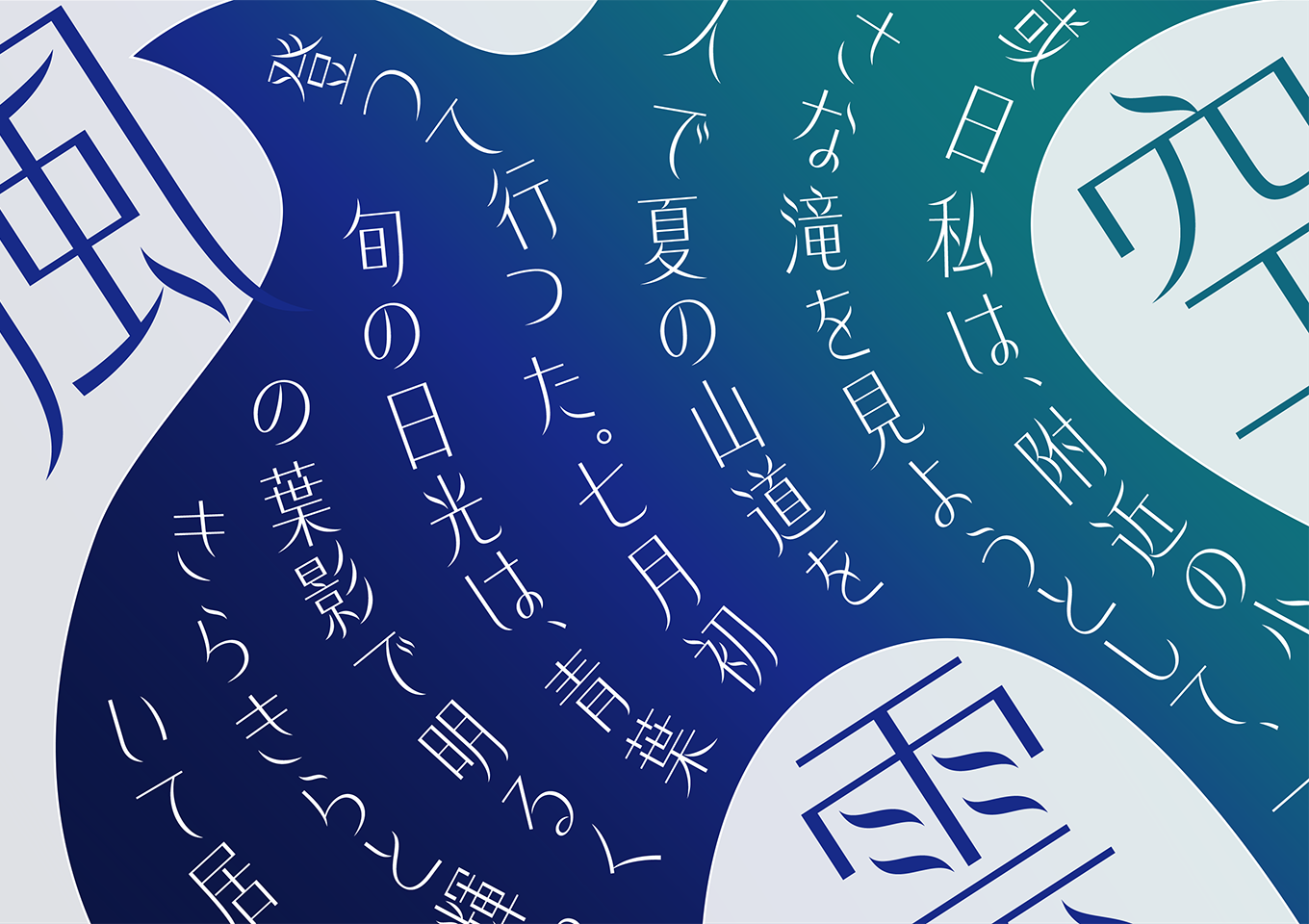
風、舞い落ちる葉、揺れるススキなど自然をモチーフにして設計されたデザイン書体です。長体の骨格と繊細でシャープなラインが特徴です。水平垂直に整備された縦画・横画と、ハライや点画に見られる滑らかな曲線のエレメントの組み合わせが、涼やかで洗練された印象を与えます。ポスターやパッケージなどの見出しで効果的にお使いいただけます。なお本書体は台湾のデザイン事務所「玉川設計所」が手掛ける繁体字フォント「風體 Wind Font」をベースに制作しています。